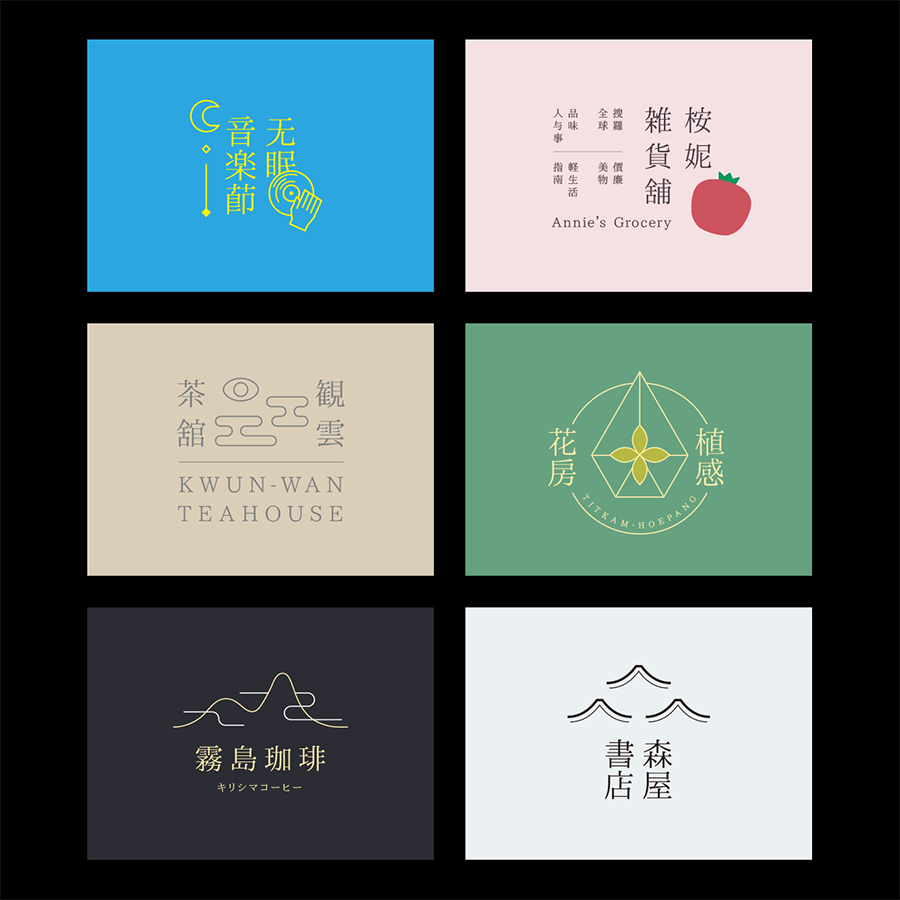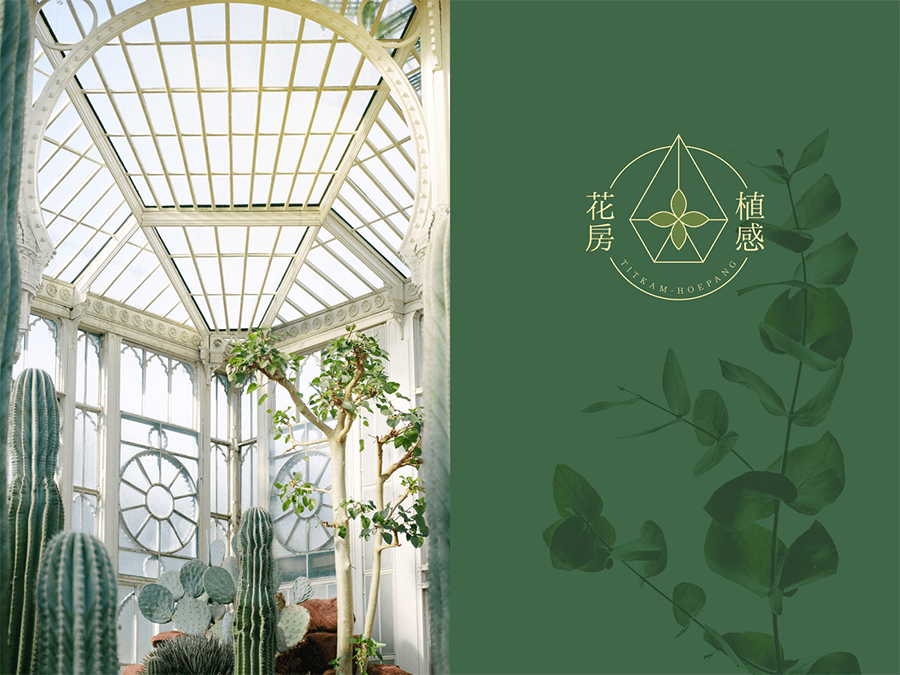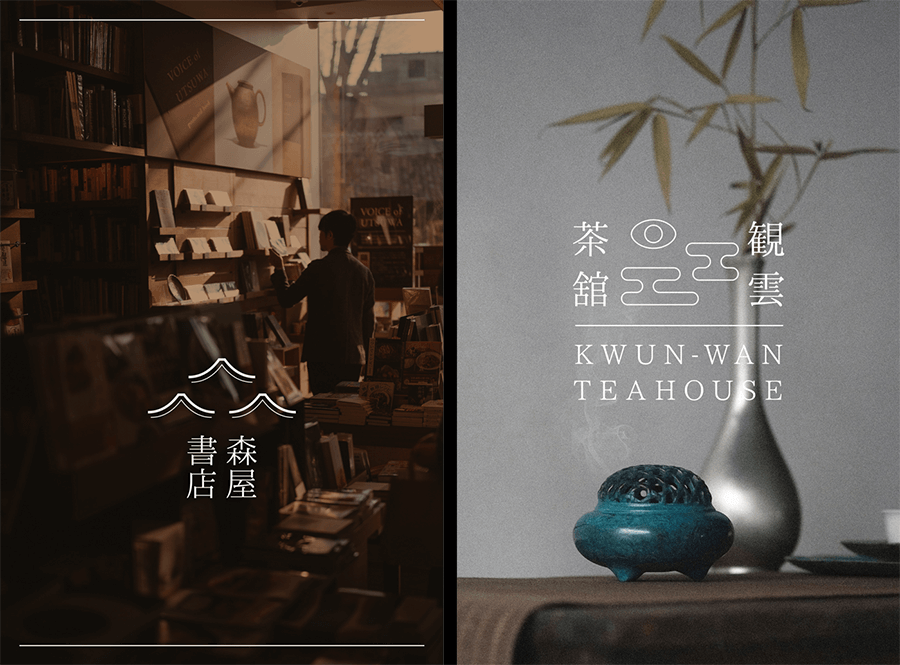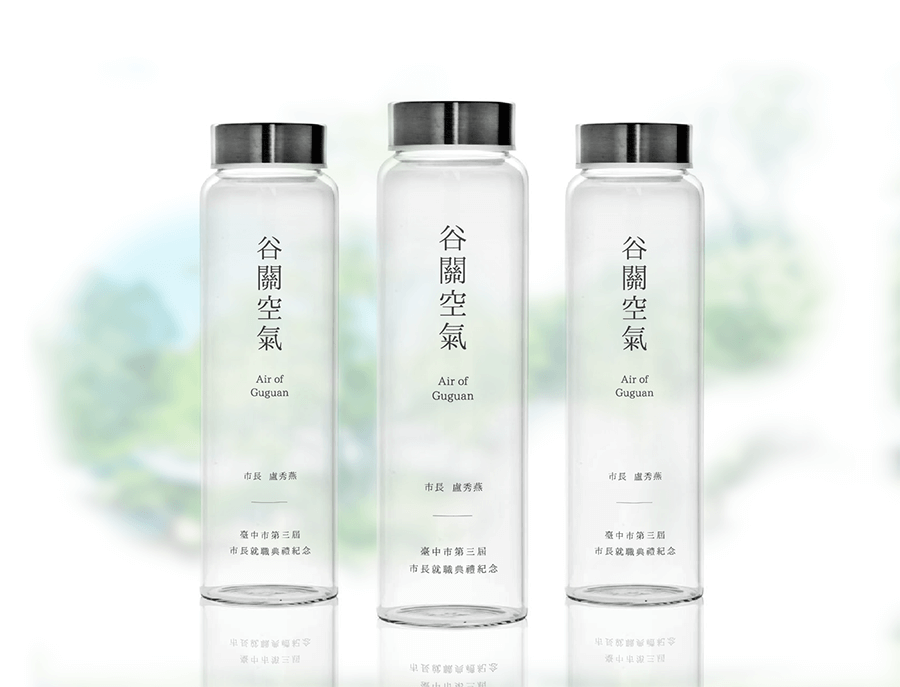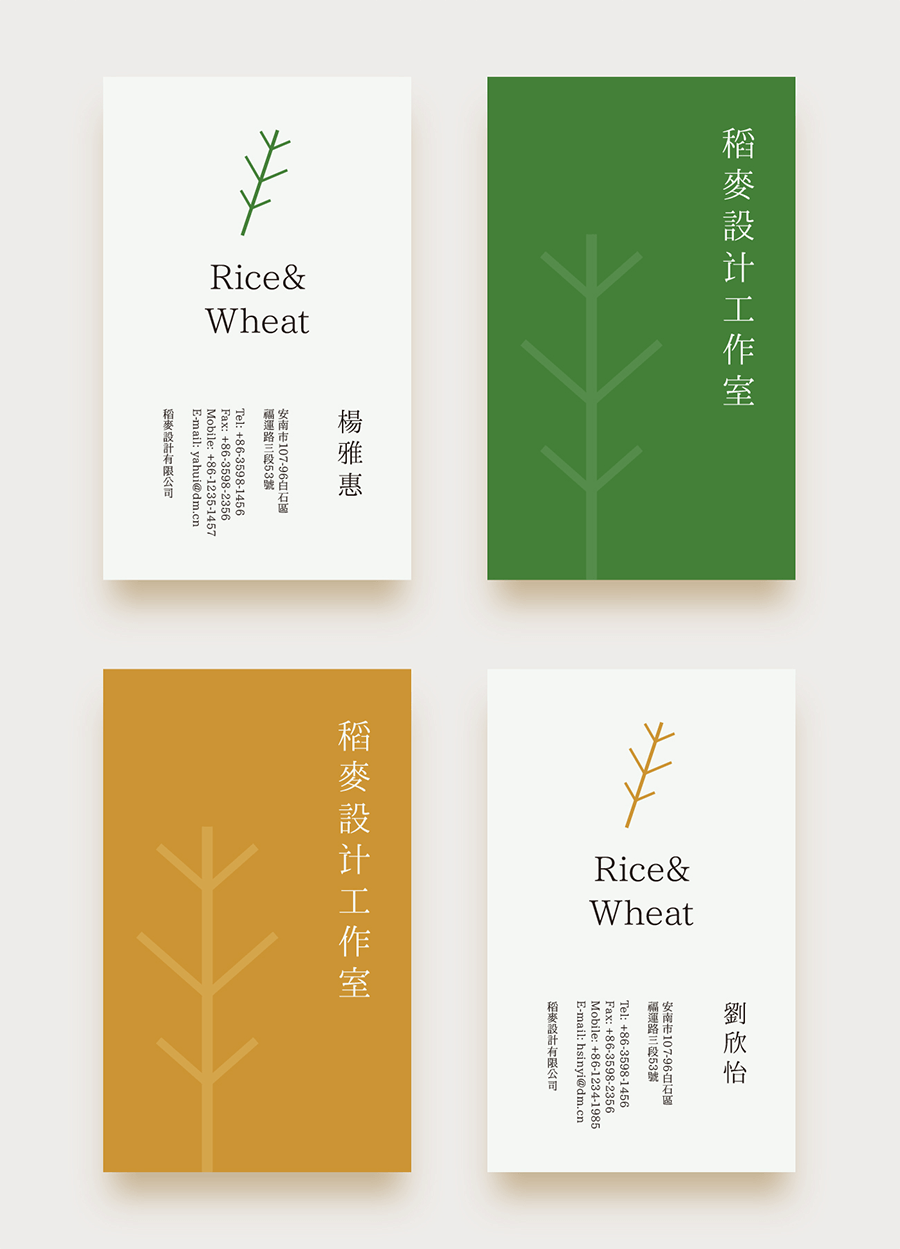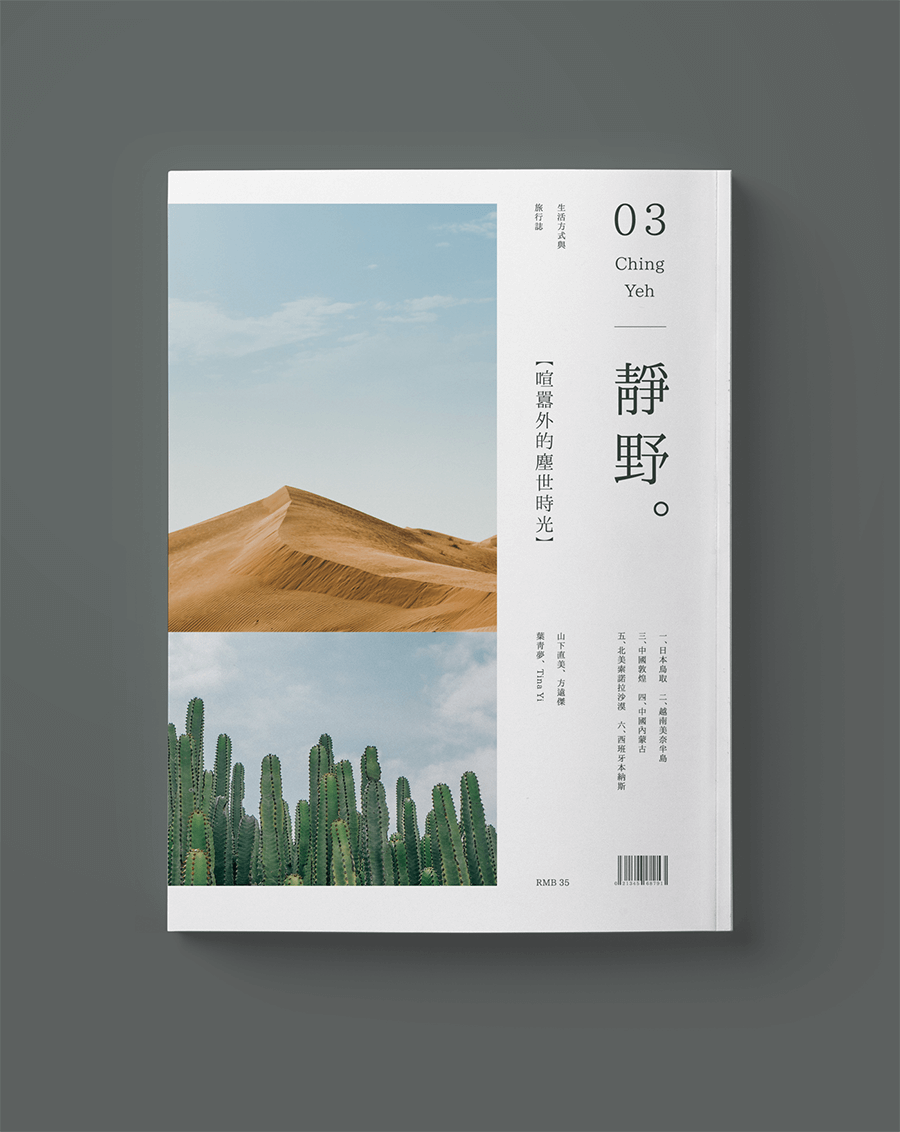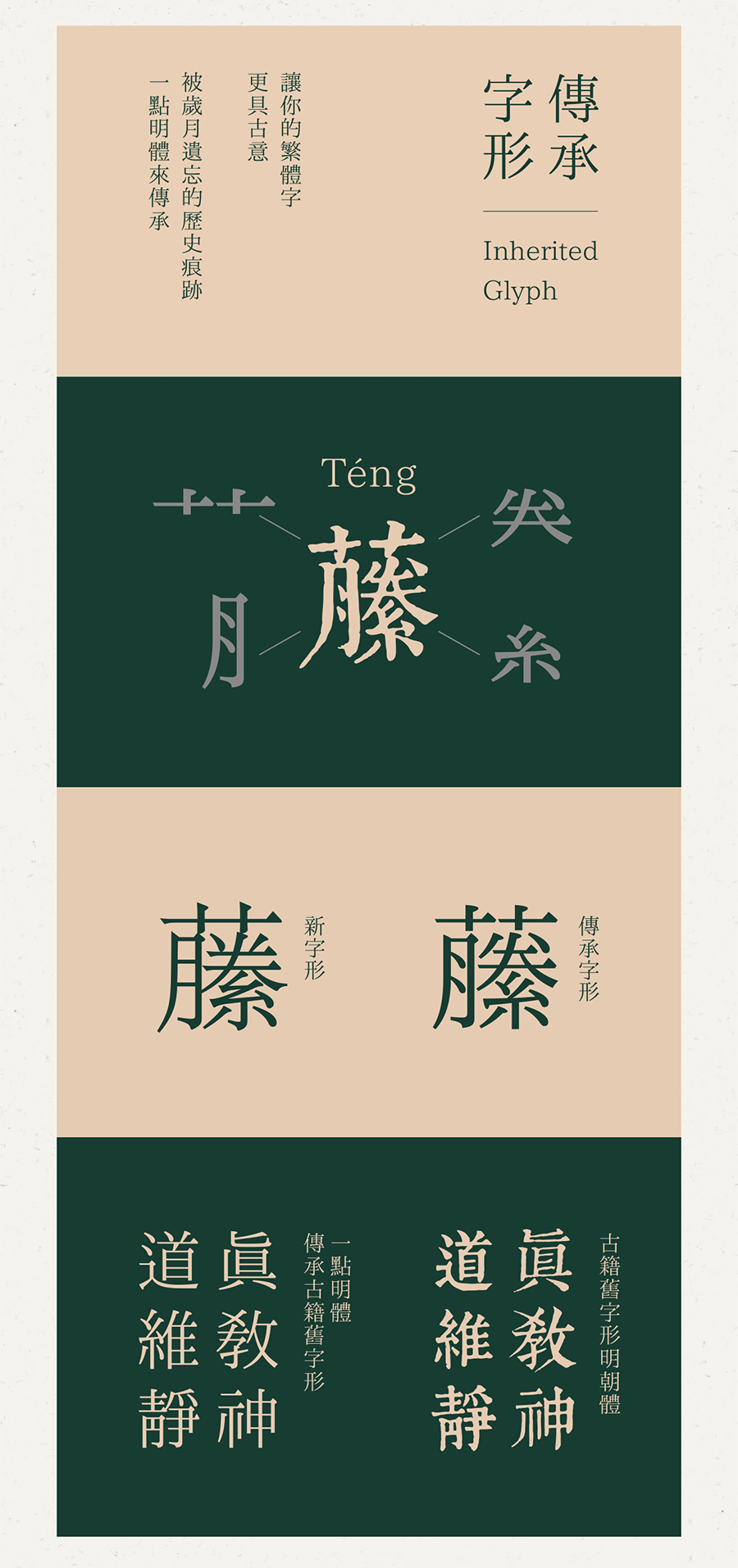
字体介绍
「I.明体(I.Ming)」乃系一套依照传承字形标准化文件《传承字形部件检校表》的推荐字形标准,并以TrueType格式封装、依照Unicode编码的OpenType字型。
我们希望「I.明体」可以作为实际示范,让大家明白制作字型时,可以采用依照传承字形标准化文件推荐字形,同时仍然依照Unicode编码、符合OpenType技术,并期待各字型厂商、字型制作者都能仿效,推出更多开源或商业市场上的传承字形字型,以收抛砖引玉之效。
「I.明体」这字型名称里的「I」是罗马数字「一」,「I.」念作「一点([粤]Jat1 dim2、[中古]Qit temq、[客]Jit7 diam3、[北]Yī diǎn、[日]いちてん、[英]One-dot)」,象征笔画的基本:点与线。
信念
汉字,在当今语文中,地位无可取代。它是唯一广泛通行的意音文字(logogram),每个构字有其字理依据,可上追字源,追踪每个汉字背后的故事。由龟甲兽骨、钟鼎礼器上图形味甚重的汉字,发展至今天,汉字展现了多变的外貌。
现在,进入了资讯爆炸的社会,汉字仍不失其生命力。今天大家使用的汉字,主要有两大类:一是手写体,由前人的楷书、行书书法演变而来,讲求灵活的变化,展示执笔者的修为,营造行间的气韵;二是印刷体,亦活跃于各种电子屏幕,上宗中国蓬勃且领先全球的印刷术里,所使用的雕版及活字造形,讲求其清晰、理性,结构稳重而明目,笔画井然且有理。
按类别不同,两种字在笔画表现上,一向有所差异。手写求活,有些笔画趋于书写时的便易;印刷求精,笔画大多保留传统理性。因此,印刷体的传承文字,本以致力保留字理为正道。
「I.明体」依照传承字形标准化文件《传承字形部件检校表》的推荐字形标准制作,力求遵从字理,展现传承汉字构字的科学系统。同时,我们另备「I.明体异体」,呈现传统印版字中常见的异体。
历史
「I.明体」经过许多人的努力才诞生。其前身是「IPA字型」。
2009年,日本「IPA」以符合「开放原始码促进会(Open Source Initiative)」开源定义的「IPA开放字型授权条款」,发布两款「IPA字型」,分别为「IPA明体(IPA明朝)」及「IPA黑体(IPAゴシック)」。字型衍生自林隆男(Takao Hayashi)所设计的两款字形: TypeBank公司的「TB明体」和「TB黑体」。字型包含了日本常用的字元,以供日本人使用。
后来,经过多年的持续修补及修订,「IPA明体」扩充成 「IPAex明体」、 「IPAmj明体」。在「IPAmj明体」里,正体汉字部份已补完得颇齐全,只是仍有少数常用字缺字。预设显示的写法仍以日文为主,字型同时收录了许多异体写法,惟须采用特定程式方能显示。其2013年11月的版本,收录了CJK基本汉字18072个,扩展A汉字5765个,扩展B汉字25320个,扩展C汉字380个,扩展D汉字108个,未映射的异体等汉字9065个。
2013年底,Halasjack公开释出「IPA明体补字」,在「IPAmj明体」的基础上,修改了部份日文写法为中文写法,把异体字里符合中文原体写法,改为预设显示的字元。他又用正体字替代缺少的简化字。当中「一简对多正」的字,如「发」、「历」等,Halasjack增补了字元,不用某个正体字代替,以免出现别字。此外,Halasjack又自造了百余个GB2312的缺字,使字型能够完全显示GB2312汉字,虽然部份简化字显示作正体字,但已能满足大陆使用者的一般需要。字型并含有部份A区和B区汉字。
2014年年中,「I.字坊」(一点字坊)处理人内木一郎开始以「IPA明体补字」为基础,增补、修改及整理字元,制作成「I.明体」,以应付正体(繁体)中文的需求。后来,幸得陈辉恒、李尔枞加入,大家一起倾力制作及修改字型档案。同时,又得Extc、钟启尧、陈志泓、佟蓝歌等同寅提供各方面的支援,李擎宇、伍梓豪、鲲逰白圭、夜煞之乐、落霞孤鹜等协助制作简化汉字,使「I.明体」字型日趋成熟。目前,「I.字坊」各同寅已补完了所有Big5汉字、GB2312汉字、IICore汉字、《通用规范汉字表》汉字,以及《常用香港外字表》第1.8版中所有字元、 「再会豆腐字」《本土语言外字表》2020年版所有字元、《康熙字典》所有字头、 jf 7000 当务字集所有汉字,此外还制作了部首及补充部首、笔画、注音符号及注音符号扩展、苏州码子、麻雀牌、中国象棋、中国算筹、中式「正」字计数符号、八卦、易经六十四卦、太玄经八十一卦等字符、多种常见汉语族语言拼音所需的字符,覆盖绝大部份正体(繁体)中文文本所使用的字元,满足香港和台湾使用者的一般需求。 「I.字坊」同寅亦进一步修改汉字写法,依据传承字形标准化文件,以传承下来的原体写法(一般来说,日本地区通称「康熙字典体」,大陆地区俗称「旧字形」)为依归。这种写法最能保留汉字字理,亦符合正体地区人士多年的阅读习惯,更能使字元设计得较美观。
下面这个图统计了这款字体里面包含多少个简体字数和繁体字数等信息,方便大家直观地了解这款字体的简繁字体数量。中国大陆的小伙伴只需特别关注GB2312和3500字常用汉字表的数量就可以了。
字体设计理念
字体样式
补完所有《常用香港外字表》第1.8版的汉字、所有「再会豆腐字」《本土语言外字表》2020年版的汉字、所有《康熙字典》字头、jf 7000 当务字集所有汉字,新增、修改个别汉字。此外,依常见欧美语文、国际音标、希腊字母、西里尔字母、多种汉语(包括官话普通话、粤语广州话、闽南语泉漳腔台语、客家语等)的拼音等排版需求,补完所需字符,处理字型档设定及OpenType技术。同时,也全面修订希腊字母、西里尔字母、国际音标符号的基线、字高、x字高、字距,新增上下标、小型大写字母功能字符。不少简化字也为美观而调整过。除了一般版、标点置中版外,更首次加入跟Windows系统细明体相同行高的「新一点」版本。